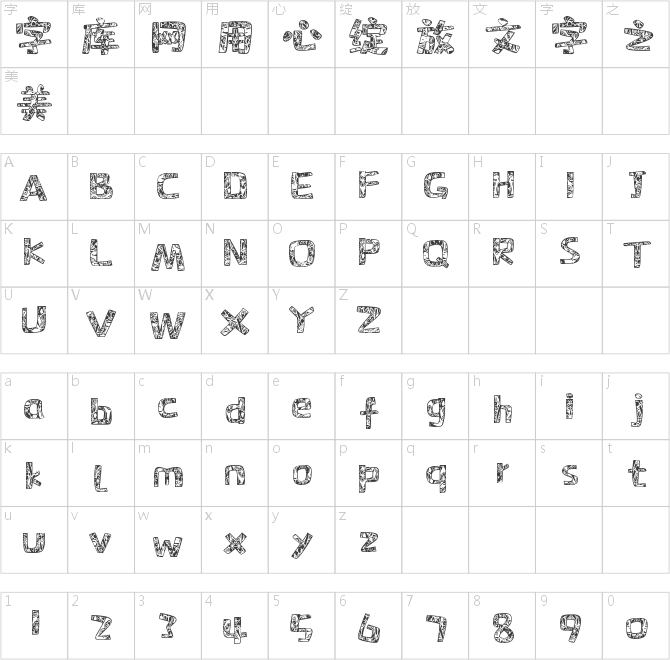
字魂153号-如意剪纸体
字魂153号-如意剪纸体字体是一款可商用的创意,创意体字体,该字体包含6763个中文、字母、符号和数字,具有中国风的风格,可以满足您设计上的各种需求,该字体主要用于标题等场景
字魂153号-如意剪纸体字体zihun153hao-ruyijianzhiti字库是一款让人赏心悦目、百看不厌的中文字体,适合各类广告和产品包装设计应用,字体大小42.92MB,格式为ttf字体,上传用户是rose,作者/版权方为字魂